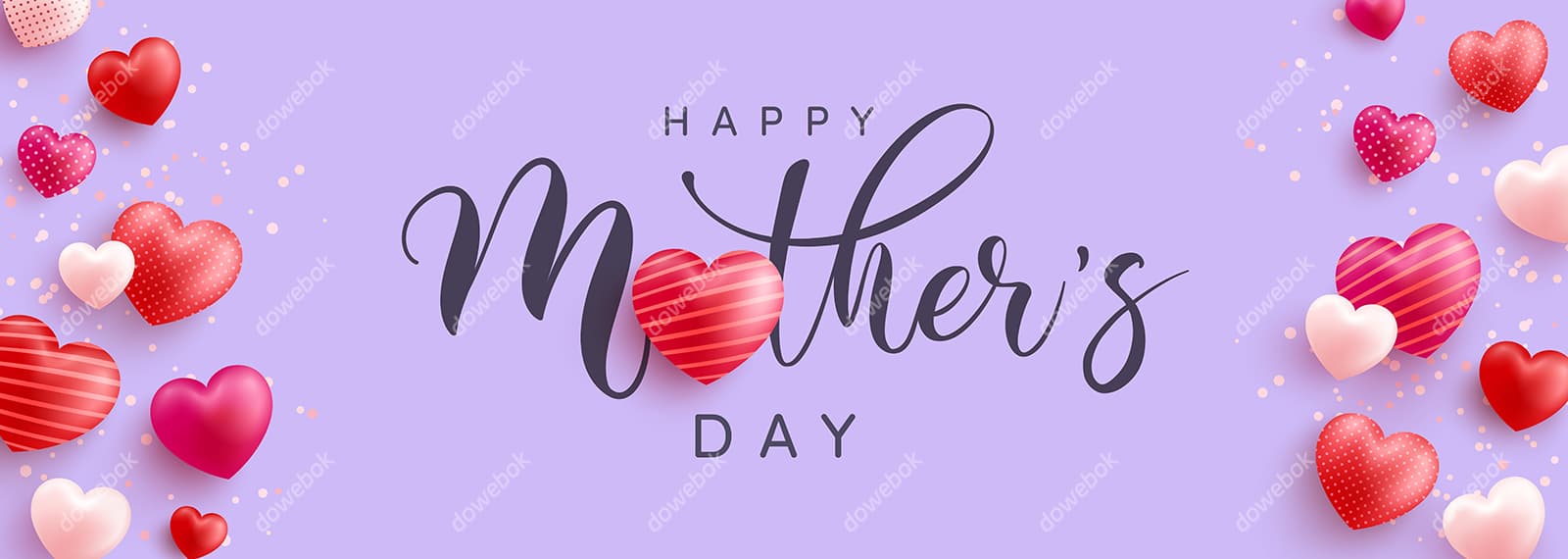
这是一款由粉色爱心和 Happy Mother’s Day 字母设计的母亲节图片素材,图片以淡紫色为背景,中央是手写风格的 “Happy Mother’s Day”,其中 “Mother’s” 的 “o” 被设计成红色条纹心形。画面左右散落着多彩的心形图案,有红色、粉色及带条纹、波点的样式,增添了节日的温馨与爱意,整体传递出浓浓的母亲节祝福。